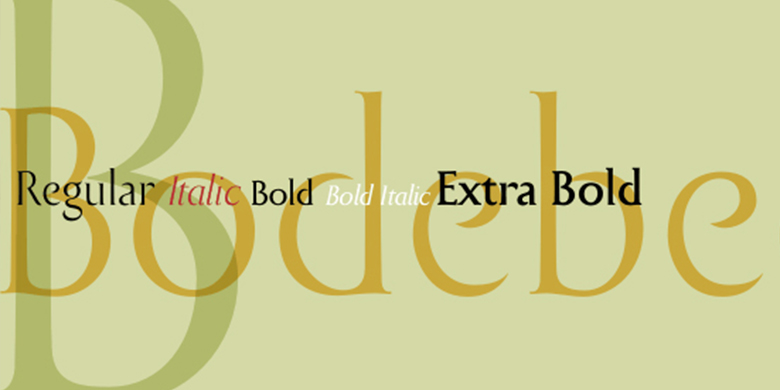
品牌:Linotype(Monotype)设计师:Bodebeck,Anders发行时间:2020字库编码:Unicode分类:衬线体字体属性:
2002年,瑞典设计师兼印刷工人Anders Bodebeck设计了Bodebeck字体家族。这个家族包括五种不同的风格,主要用于标题或显示字体,属于新过渡风格的字体。18世纪50年代后期,英国首次出现了过渡型字体,当时John Baskerville发布了他的第一套字体。Bodeck与另一种后来过渡风格的字体也有相似之处——Eric Gill的Perpetua (1928年由英国Monotype公司发行)。
就像之前的两位英国石匠变成了排版大师一样, Anders Bodebeck给我们带来了对经典字体的现代重新诠释。Bodebeck配有老式的人物造型,有以下几种样式可供选择: Regular、Italic、Bold、Bold Italic以及Extra Bold。”
The Swedish designer/typographer Anders Bodebeck designed the Bodebeck type family in 2002. The family, which includes five different styles, is primarily intended for use as a titling, or display face, and belongs to the neo-transitional style of typefaces. Transitional style type first appeared in England during the late 1750s, when John Baskerville released his first sets of type. Bodeck bears similarities to another, later transitional style typeface as well – Eric Gill’s Perpetua (originally released by the British Monotype Corporation in 1928).
Like these two previous English stonecutters turned masters of typography, Anders Bodebeck has given us a modern re-interpretation of classic letterforms. Bodebeck, which is fitted with old style figures, is available in the following styles: Regular, Italic, Bold, Bold Italic, and Extra Bold."